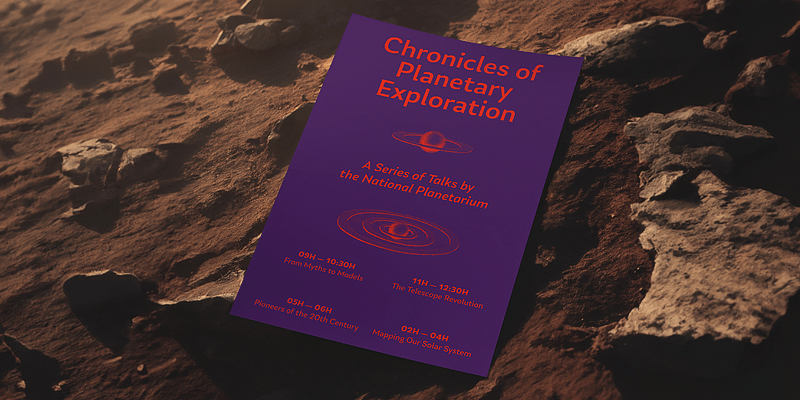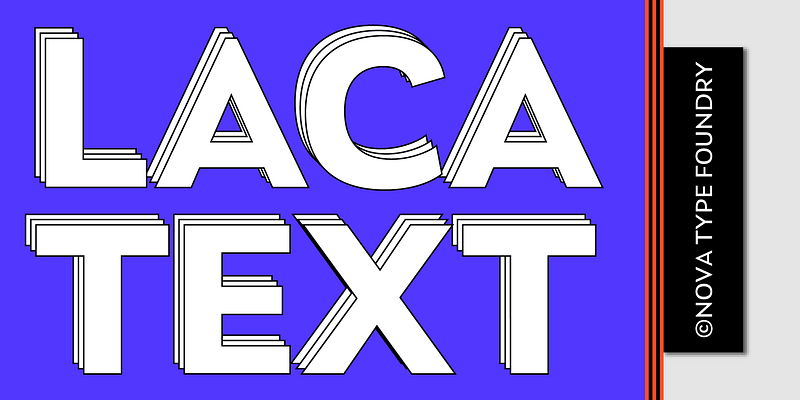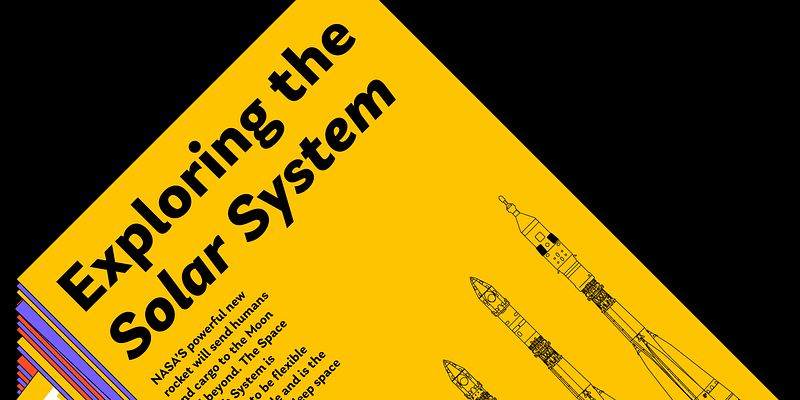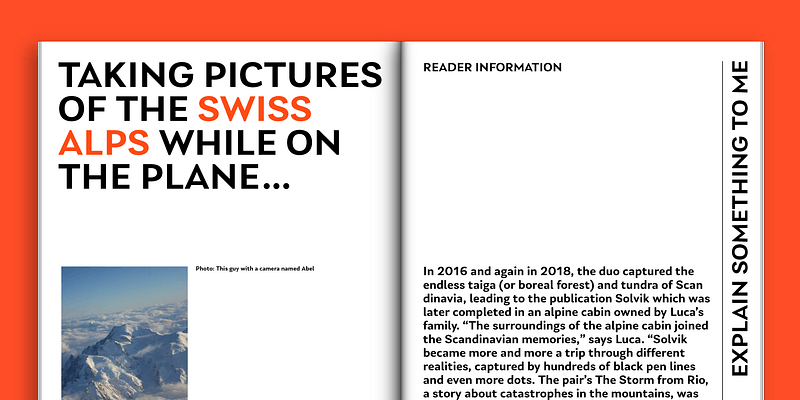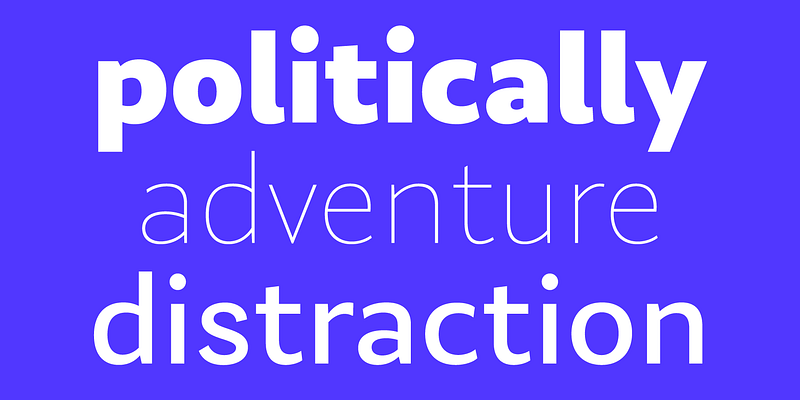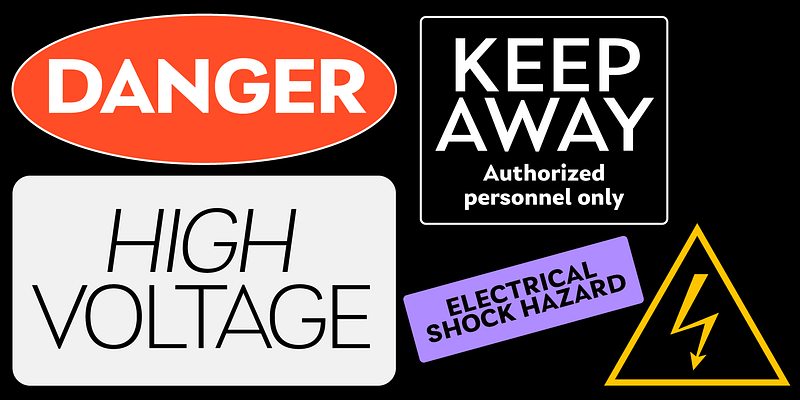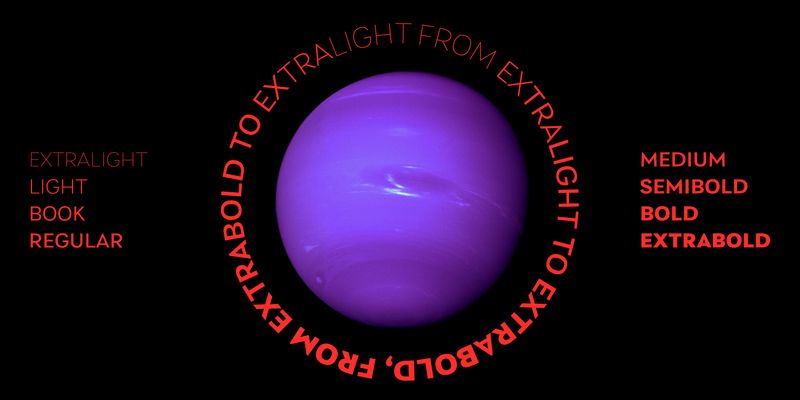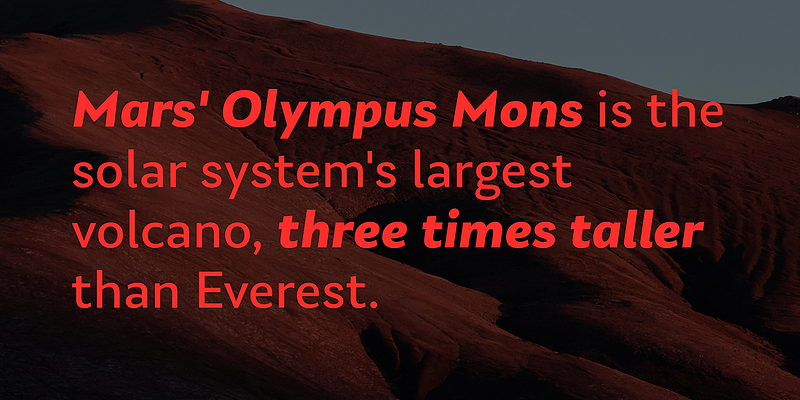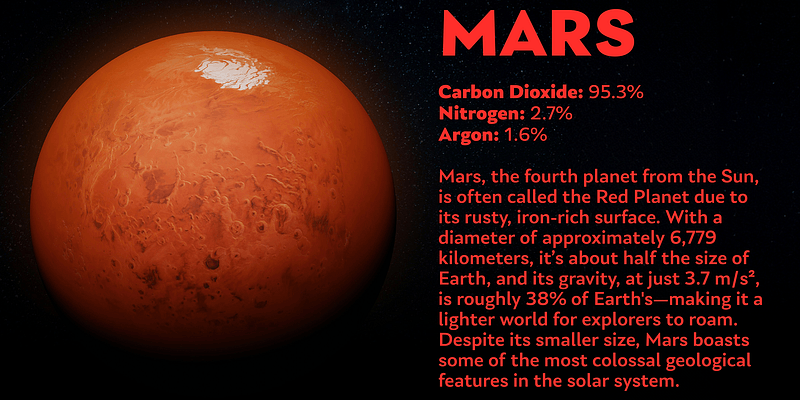
Laca Text est une version sans empattement de la police Laca. Elle a été conçue à partir des formes de base de Laca. Elle a des caractéristiques comme une hauteur d’œil élevée, des contrepoinçons ouverts et des jambages inférieurs. Laca Text est idéal pour les textes longs et l’image de marque.